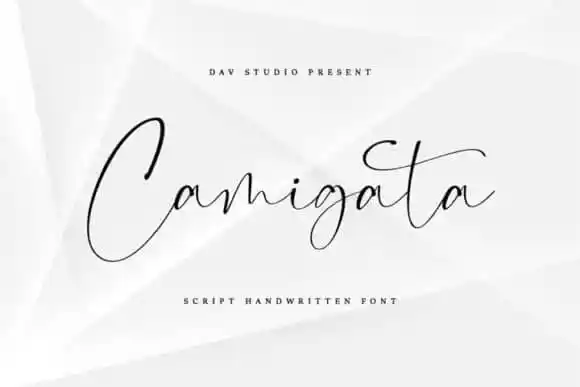
Camigata Handwritten Font – Download Grátis
A Camigata Handwritten Font é uma elegante fonte escrita a mão que inclui suporte para múltiplas línguas. Suave e delicada, esta fonte oferece um conjunto completo de letras maiúsculas e minúsculas incrivelmente bonitas, números e um extenso seleto de sinais gráficos. A Camigata é uma criação do designer Dav studio da 99designs. Com personagens bem equilibrados e cheios de beleza, ela combina perfeitamente com diversos estilos de design. Aumente suas ideias criativas adicionando esta fonte a elas; notarás como ela as faz realmente viver! A Camigata é ideal para aqueles que procuram um touch pessoal em seus projetos, sejam eles logos, cartazes ou qualquer outro tipo de arte. Este é o ideal para quem procura uma escrita elegante e encantadora.